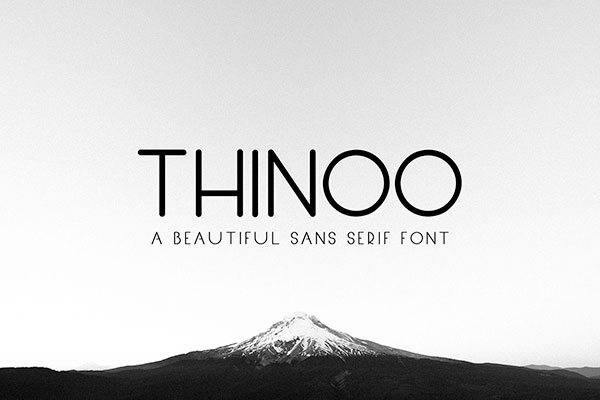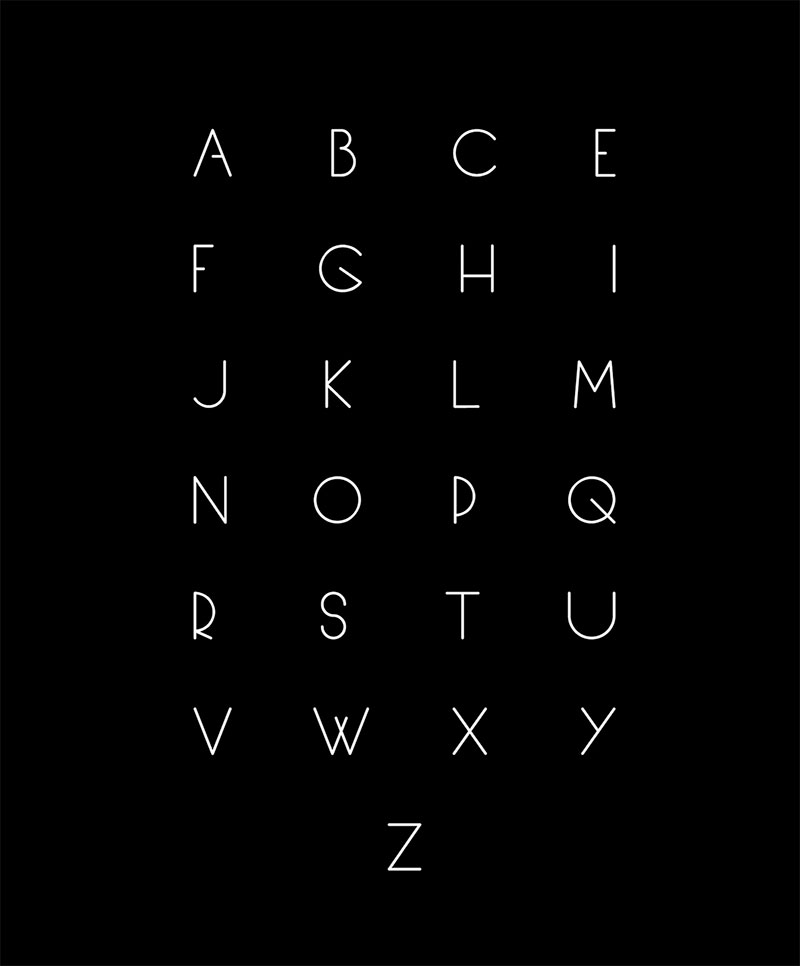
THINOO字体
Thinoo是一款由巴基斯坦设计师Nauman Altaf创作的免费sans serif英文字体,呈现出干净而现代的风格。字体样式纤细而醒目,包含大写、小写、数字、标点和符号,适用于多种场合。无论是简历、徽标、网站、品牌材料、T恤、印刷品、名片、海报、摄影还是女性产品等方面,Thinoo都能发挥出色的作用。
Thinoo字体包含thin和bold两种粗细,虽然以“thin”命名,但实际上bold版本依然非常纤细。这款字体由作者在Behance平台上发布,并声明个人及商用免费。优质模板网认为,这款字体将为您的设计作品增添现代而清新的视觉效果,使您的创意得以充分展现。
THINOO效果预览